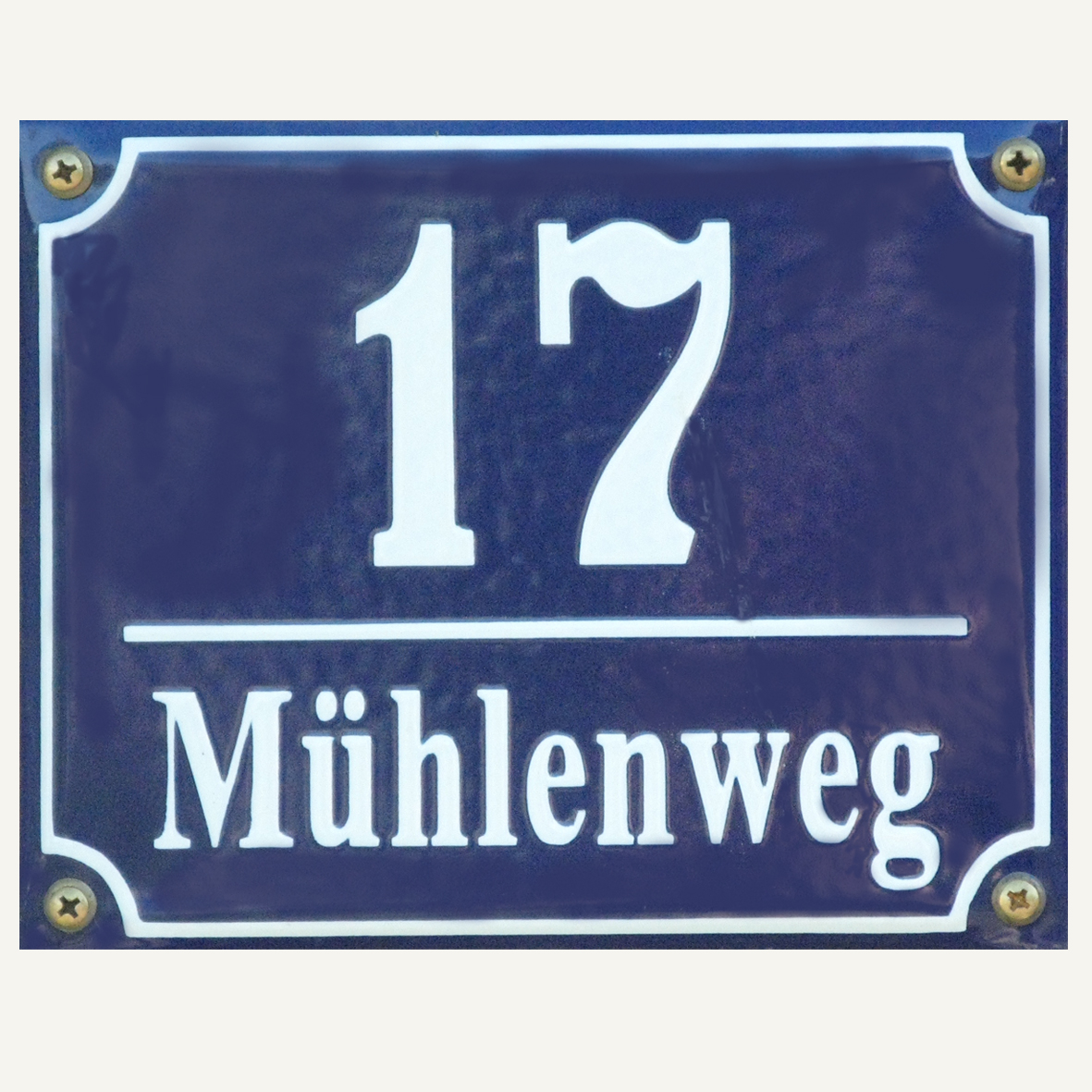
Schrift von Emaille-Hausnummer gesucht.
Ein Freund fragt das, ich kann ihm aber leider nicht helfen. Ideen? Sieht ja eher neu aus …
Ich hatte ja eher an jene gedacht:
... und dann nochmal ein bisschen gedrückt und gestopft, damit sie auf das Schildchen passt. Aber die Serifen passen nicht wirklich ...
aber die Zahlen sind so ganz anders …
"Schillerplatz Reg" ist wohl auch "nur" aus einem Emailleschild abgeleitet – waren das früher alles Handarbeiten?
Habe Google mal Löcher in den Bauch gefragt und ein paar interessante Seiten gefunden, auf denen man sogar heutzutage noch mit Handarbeit gefertigte Emaille Schilder bestellen kann! Früher war es wahrscheinlich nicht anders - nur, dass man nicht via Internet bestellt hat, sondern zum Laden hin ist und dort vor Ort bestellt hat.
Sieht fast so aus, ja.
Ich schätze mal, dass diese Emailschilder-Hersteller da nicht auf digitale Satzschriften neuen Datums zurückgreifen, sondern noch immer die alten, damals handgeschnittenen Pappschablonen verwenden. Im Grunde, wie wir es ja bei der Linzer Straßenschilder-Schrift durchgegangen sind. Daher dann auch von Ort zu Ort die oft leicht abweichenden Schriftformen, die sich, besonders bei Schildern aus der Vor-Internet-Zeit quasi das Stadtbild prägen, da diese zumeist beim örtlich nächstgelegenen Schilderproduzenten bestellt wurden.
Ich erinnere mal an das hier:
Aber lagen den alten Pappschablonen keine Satz- oder Displayschriften zugrunde?
Möglich, aber nicht unbedingt. Wie sich ja bei der Linzer Straßenschilderschrift gezeigt hatte, war diese ja extra für diese Anwendung entworfen worden. Und so gab es eben vor den digitalisierten Schriften, die heute ein und die selbe Schriftart für alles mögliche verwendbar macht, ungeachtet ob diese sich für auch alle Anwendungen eignet eben sehr unterschiedliche Schrift-Universen, je nach Branche. So gab es eben Schilderschriften der Emailschrift-Fabrikanten, Schildermaler-Schriften, welche von Hand an die Wand gepinselt wurden. Plakatmaler-Schriften, die sich davon wieder unterschieden, Steinmetz-Schriften, die auch oft von künstlerisch und kalligrafisch begabten im Steinmetz betrieb gezeichnet wurden. Sicher inspiriert von Drucksachen, aber dann eben nicht abgepaust und mit dem Storchenschnabel auf die benötigte Größe gebracht, sondern eben nur ähnlich der Vorlage unter Berücksichtigung der Erfahrungen mit dem jeweiligen Material  relativ frei nach gezeichnet, oder gar komplett nur dem Stil der Druckschrift folgend frei gezeichnet.
Wir kennen ja die meisten der Schriftgestalter der Schriftgießereien, wenn da die Schrift nicht einfach als "Hausschnitt" bezeichnet war und der Feder (oder dem Bleistift) eines talentierten Mitarbeiters entstammte. Aber so wie es in diesem Gewerbe talentierte Schriftgestalter gab, so gab es sie eben auch in anderen Berufssparten - Überschneidungen hierbei aber nicht ausgeschlossen. Aber auch wenn Schriftgestalter, die für Schriftgießereien arbeiteten auch eine Schilderschrift für die örtlichen Straßennamen entwarfen, unterscheidet sich dieser Entwurf, den Einschränkungen aber auch Möglichkeiten des anderen Mediums folgend von den Entwürfen für die Bleischriften.
Für mich sind übrigens gerade diese nie in Blei gegossenen Schriften die wirklich interessanten, denn hier finden sich Schriften für andere Anwendungen, bei denen gängige Satzschriften oft nicht einmal richtig passen, und dann einfach linear für eine Wandanschrift vergrößert einfach falsch wirken.